Genderzeichen
Unter »Genderzeichen« werden in der Typografie typografische Satzzeichen (Sonderzeichen) bzw. orthografische Satzzeichen (Interpunktionszeichen) verstanden, die im Sinne einer geschlechtergerechten Sprache zwischen männlichen, weiblichen und auch nichtbinären 1) bzw. diversgeschlechtlichen 2) Personen in Form einer gendergerechten Schreibweise als Platzhalter in Personenbezeichnungen (z.B. Ingenieur:in) dienen.
Genderzeichen stehen seit ungefähr den 2000er Jahren für eine geschlechtsneutrale Verwendung maskuliner Substantive oder Pronomen. Sie sind (buchstäblich) ein Symbol für die Ablehnung des generischen Maskulinums, welches aus heutiger Sicht mehr oder weniger eine anachronistische Schreibweise in Sprache und Schrift – beruhend auf einem von Männern dominierten sozialen System – repräsentiert.
Satztechnisch sind Genderzeichen verkürzte Schreibweisen in Headlines, Copies und Fließtexten, um weibliche, männliche und diverse Paar- bzw. Trisetformen zu verkürzen und um Konjunktionen zu vermeiden, beispielsweise »Ingenieur:in« anstatt »Ingenieur und Ingenieurin«.
Zu den gebräuchlichsten Genderzeichen zählen beispielsweise Binnen-I (z.B. IngenieurIn), Doppelpunkt (z.B. Ingenieur:in), Parenthesen (z.B. Ingenieur[in]), Schrägstrich (z.B. Ingenieur/in), Sternchen (z.B. Ingenieur*in), Trema-ï (z.B. Ingenieurïn) und Unterstrich (z.B. Ingenieur_in).
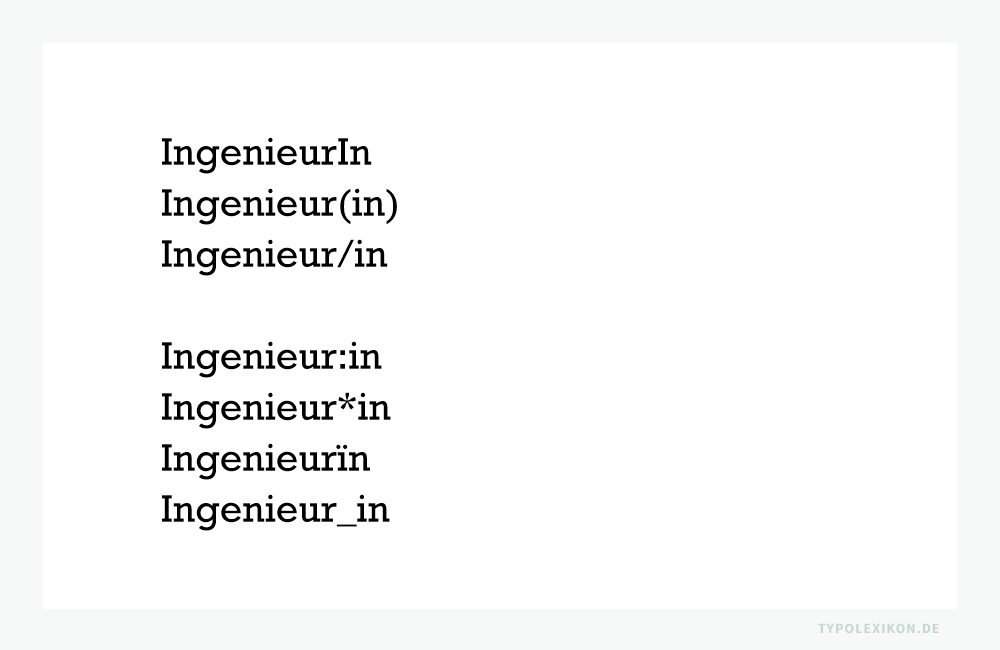
Gendergerechte Schreibweise
Grundsätzlich gilt in der Typografie, dass Abkürzungen – abgesehen von Nachschlagewerken wie beispielsweise Lexika oder Wörterbücher – in Headlines, Copies und Fließtexten nicht verwendet werden sollten. Eine typografische Faustregel lautet: Wer Platz und Zeit hat, sollte niemals abkürzen. So gesehen, dürften grammatikalisch neutrale Bezeichnungen und Formulierungen sicherlich die beste Form einer geschlechtergerechten Sprache/Schrift sein, allerdings auch die komplizierteste.
Beispiel gendergerechte Schreibweise:
Sehr geehrte Lehrer/innen > Sehr geehrte Lehrende die Mitarbeit der Studenten/innen > die studentische Mitarbeit
Beidnennung
Die sogenannte »Beidnennung« ist die vollständige Paarform im Singular und Plural für das männliche und weibliche Geschlecht. Typografisch betrachtet, stellt sie die unter den Paarformen (m/w) die bestmögliche Form im Sinne der Lesbarkeit dar. Dabei wird traditionell die weibliche Form immer zuerst genannt, was auch bei den abgekürzten Paarformen gilt. 3)
Beispiel Beidnennung:
Ingenieurin und Ingenieur Ingenieurinnen und Ingenieure
Problematik der Beidnennung
2017 wurde vom Bundesverfassungsgericht in Karlsruhe neben weiblich und männlich das dritte Geschlecht »divers« anerkannt. 4) In seinem Beschluss manifestiert das höchste deutsche Gericht, dass Persönlichkeits- und Gleichheitsrechte verletzt werden, wenn inter- oder transsexuelle Menschen keine Möglichkeit haben, ihre biologische Identität in anderer Form als weiblich bzw. männlich bei Behörden zu registrieren. Infolge können ab dem 22.12.2018 Personen ihre sexuelle Identität neben männlich und weiblich auch als divers bei den Behörden registrieren lassen. 5)
Beispiel m/w/d:
m/w/d = männlich/weiblich/divers
Mit der offiziellen Einführung des dritten Geschlechts stehen alle klassischen Paarformen zugunsten einer neuen Triplizität auf dem Prüfstand. Welches der nachfolgenden Genderzeichen über eine zufriedenstellende Trisetform verfügt, darüber wird zurzeit leidenschaftlich in unterschiedlichen Disziplinen und Interessengruppen (z.B. in der Politik, Sprachwissenschaft, Typografie, in der LGBT bzw. LGBTQ-Community 6) oder Theologie) nachgedacht und diskutiert. Grundsätzlich ist festzustellen, dass Genderzeichen im dspr. Raum – im Sinne von Pro und Contra – stark polarisieren, so leider auch die »Cancel-Culture« befördern. Laut einer Umfrage vom Juli 2023 lehnt die Mehrheit der Deutschen das Gendern ab. Gemäss den Angaben stören sich 73 Prozent der Befragten an Sternchen, Unterstrich, Doppelpunkt oder Sprechpausen. 7)
Verkürzte Paarformen (m/w)
Binnen-I
Das Binnen-I in Form der Majuskel »I« ist geeignet für die verkürzte männliche und weibliche Paarform. Für die verkürzte diverse Form, ist dieses Genderzeichen weniger geeignet. In der Praxis funktioniert diese Variante auch nur bei Schriften mit Serifen (siehe Antiqua). Bei serifenlosen Schriften (siehe Grotesk) ist die Verwechslung mit der Minuskel »l« naheliegend. Für den Majuskelsatz (Versalsatz) ist das Binnen-I nicht geeignet.
Für Blinde und stark Lesebehinderte wird in Sprachausgabeprogrammen, z.B. NonVisual Desktop Access (NVDA®) und Job Access With Speech (Jaws®) bzw. in Desktop-Screenreader, z.B. Android Talkback® oder iOS VoiceOver®, das »I« als »i« gelesen. Hypothese: Für Sehbehinderte, Lesebehinderte und Menschen mit Asperger und Autismus dürfte das Binnen-I vermutlich keine zufriedenstellende Lösung sein.
In der Google®-Suchmaschine wird das Binnen-I buchstabengetreu gelesen und dementsprechend werden in den Suchergebnissen »weibliche« Ergebnisse mit »i« favorisiert (Stichprobe 31.8.2021). In anderen Suchmaschinen, z.B. DuckDuckGo® oder Bing®, wird das »i« mehr oder weniger ignoriert (Stichprobe 31.8.2021).
Beim Binnen-I muss die männliche Form immer der weiblichen Endung vorangestellt werden, ansonsten funktioniert die abgekürzte Paarform nicht.
Beispiel Gender-I: